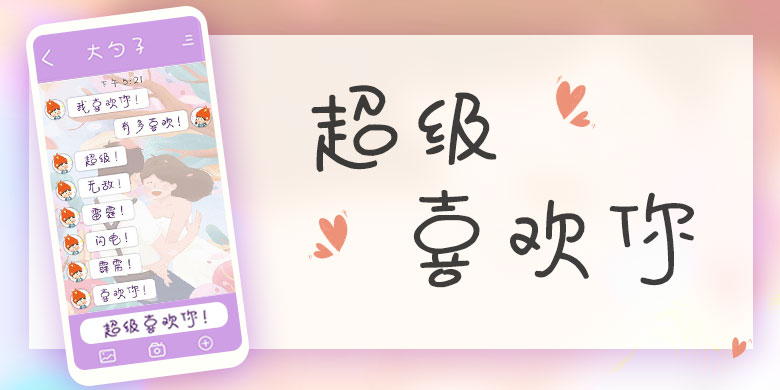
品牌:方正手迹设计师:余丹发行时间:2019字库编码:大陆简体(GB2312-80)分类:创意书写字体属性:精品字
笔画全部由等粗的直线段搭接而成,字形结构夸张,字面大小不一,字内空间充满跳跃感,折笔处呈圆角。个性顽皮可爱,放大的口如同对你的爱无限放大。适用于少年儿童类的书刊、品牌广告和产品包装设计,以及社交网络的个性化用字。